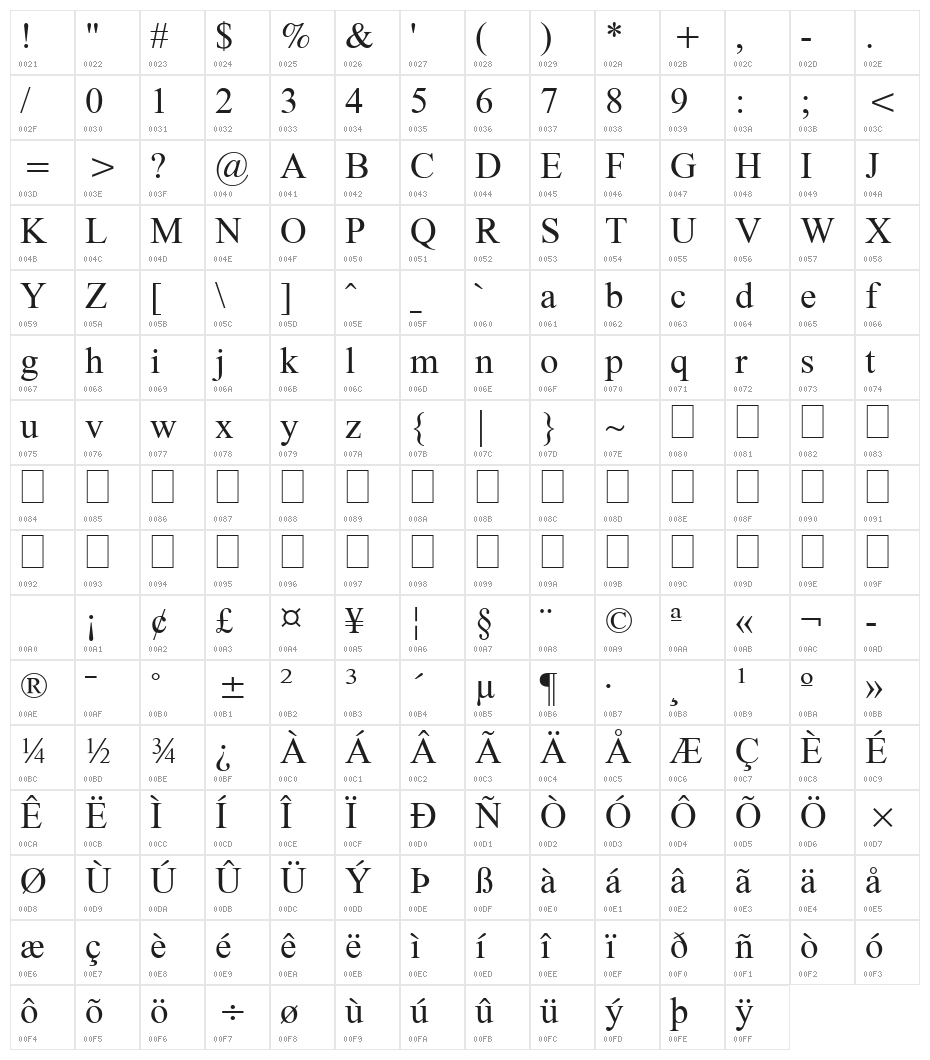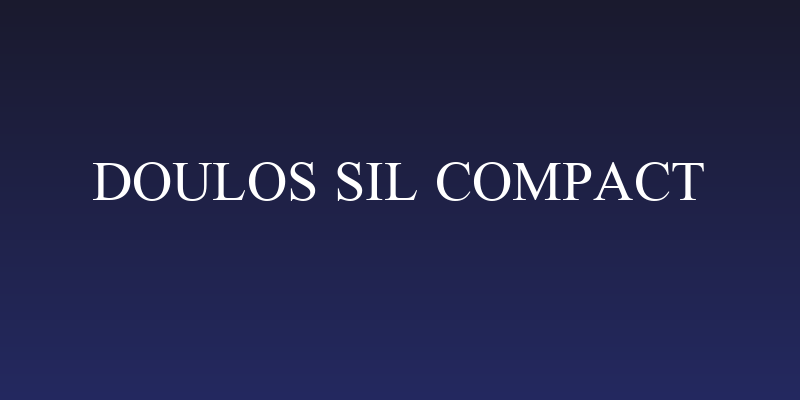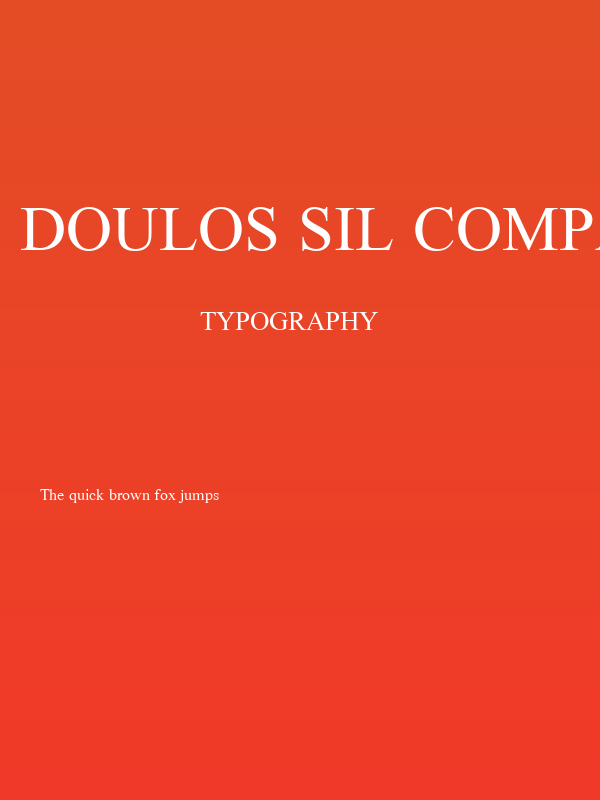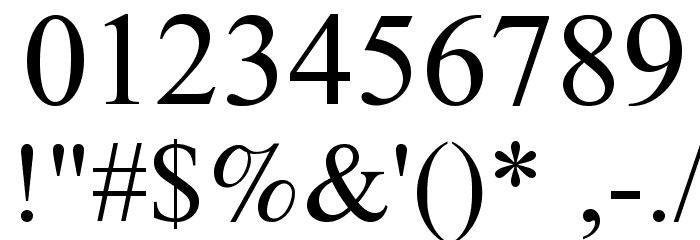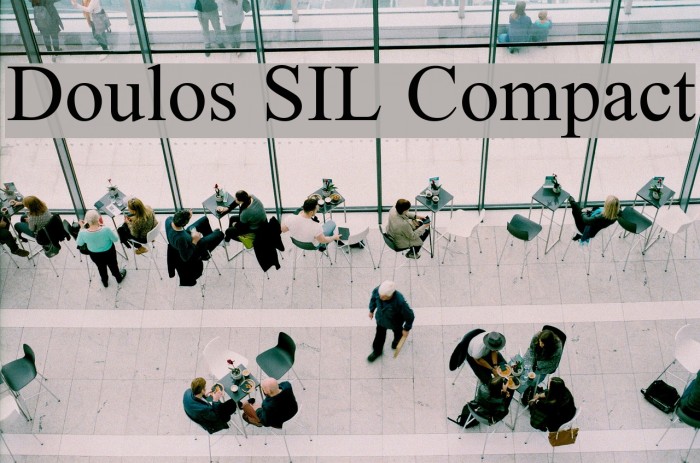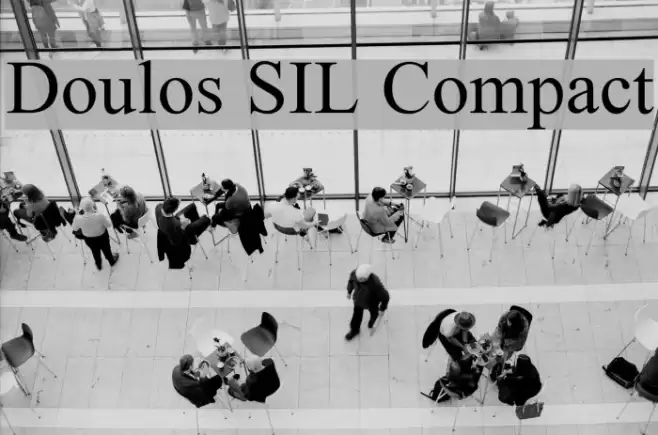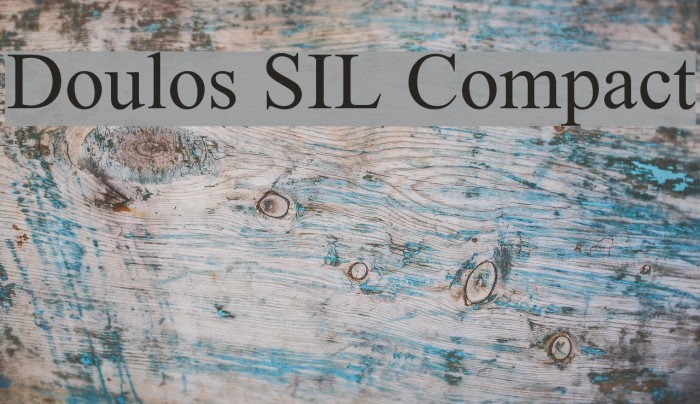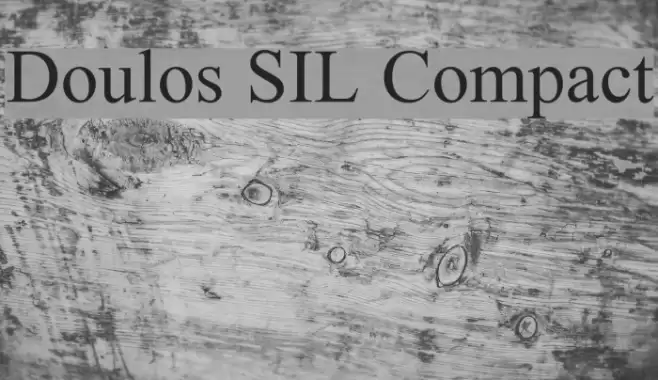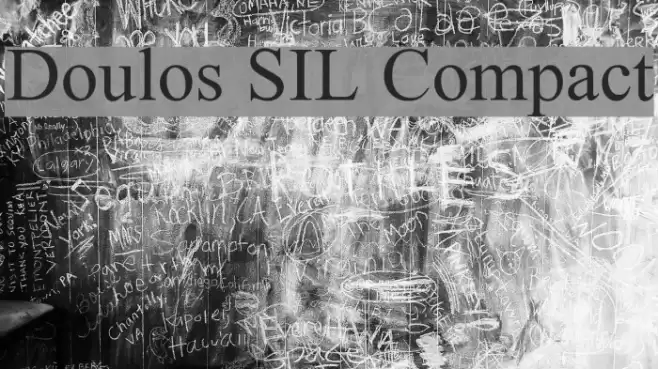
Doulos SIL Compact Font
| Caz de utilizare | Body text, Headlines, Formal documents |
| Proiecte propuse | Ideal for projects requiring a traditional and professional look, such as book typesetting, formal invitations, academic papers, and corporate branding. |